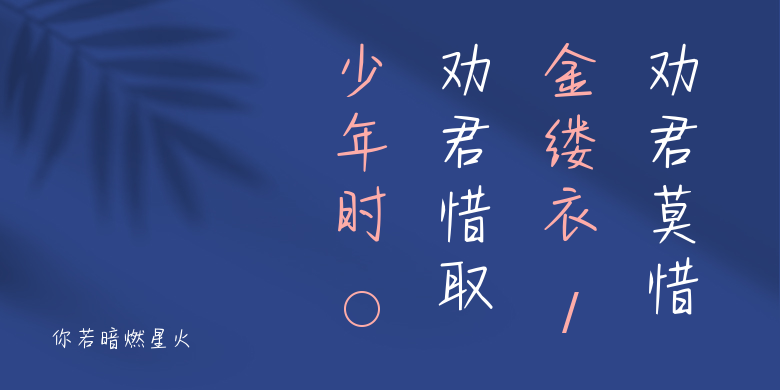
你若暗燃星火
你若暗燃星火,这款字体结构工整、笔画清晰,兼顾美观与易读性,适用于标题、正文、海报、包装、LOGO 等多种场景。字形优雅稳定,风格百搭耐看,适配日常排版与创意设计,让文字呈现更舒适、更具质感。你若暗燃星火一笔一画,皆是细节,以均衡的比例、流畅的线条打造舒适视觉体验,字形端正大气,风格简约现代。无论是商业设计、品牌宣传还是日常排版,都能轻松驾驭,让文字更有格调与力量。你若暗燃星火字体下载。